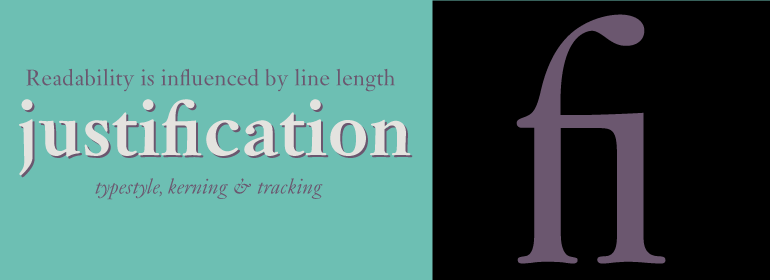
Monotype Janson®
字体品牌: Monotype 设计师:Nicholas,Robin; Saunders,Patricia 字体分类:衬线体 字体属性:外文 字符集:Unicode 发布时间: 2018
Monotype Janson字体家族是基于最初由匈牙利雕刻师Nicolas Kis大约于1690年所切割的字体。它是以荷兰印刷商Anton Janson的名字命名。原始模板于1919年交由德国的Stempel铸造厂。新字体被铸造且校样;这些被用作Monotype的Janson版本的来源。最初手刻的Janson字体具有许多小的不规则的设计,这使字体具有独特的魅力。这些已被纳入到新版本中。其整体效果是色彩均匀且易于阅读,使Monotype Janson在书籍和出版工作中最为自如。
The Monotype Janson font family is based on types originally cut by the Hungarian punch-cutter, Nicolas Kis circa 1690. Named after Anton Janson, a Dutch printer. The original matrices came into the hands of the Stempel foundry in Germany in 1919. New type was cast and proofs made; these were used as the source for Monotype's version of Janson. The original hand cut Janson types have a number of small design irregularities which give the typeface its unique charm. These have been carefully incorporated into the new version. The overall effect is of even color and an easy readability that makes Monotype Janson most at home in book and publishing work.